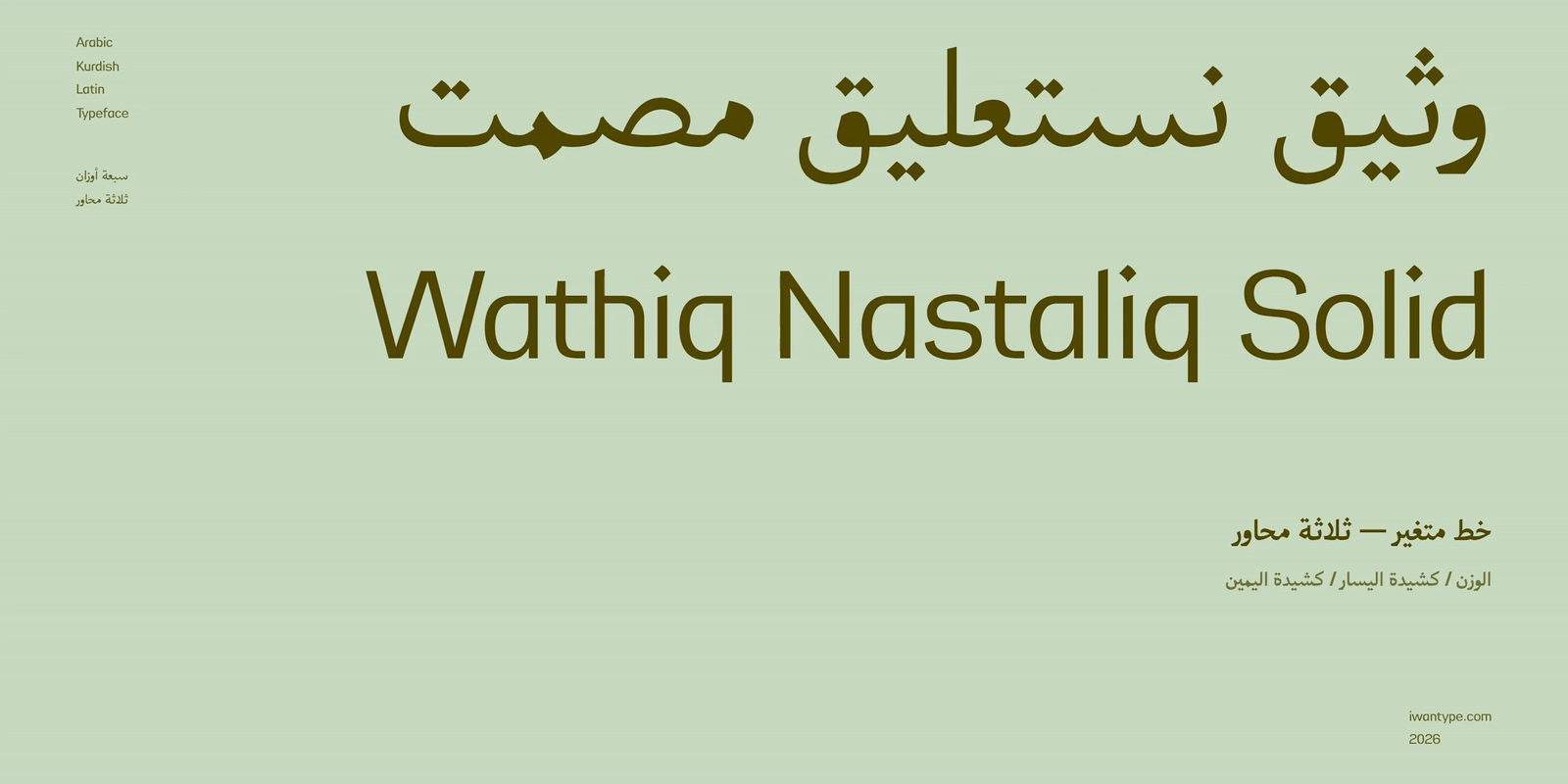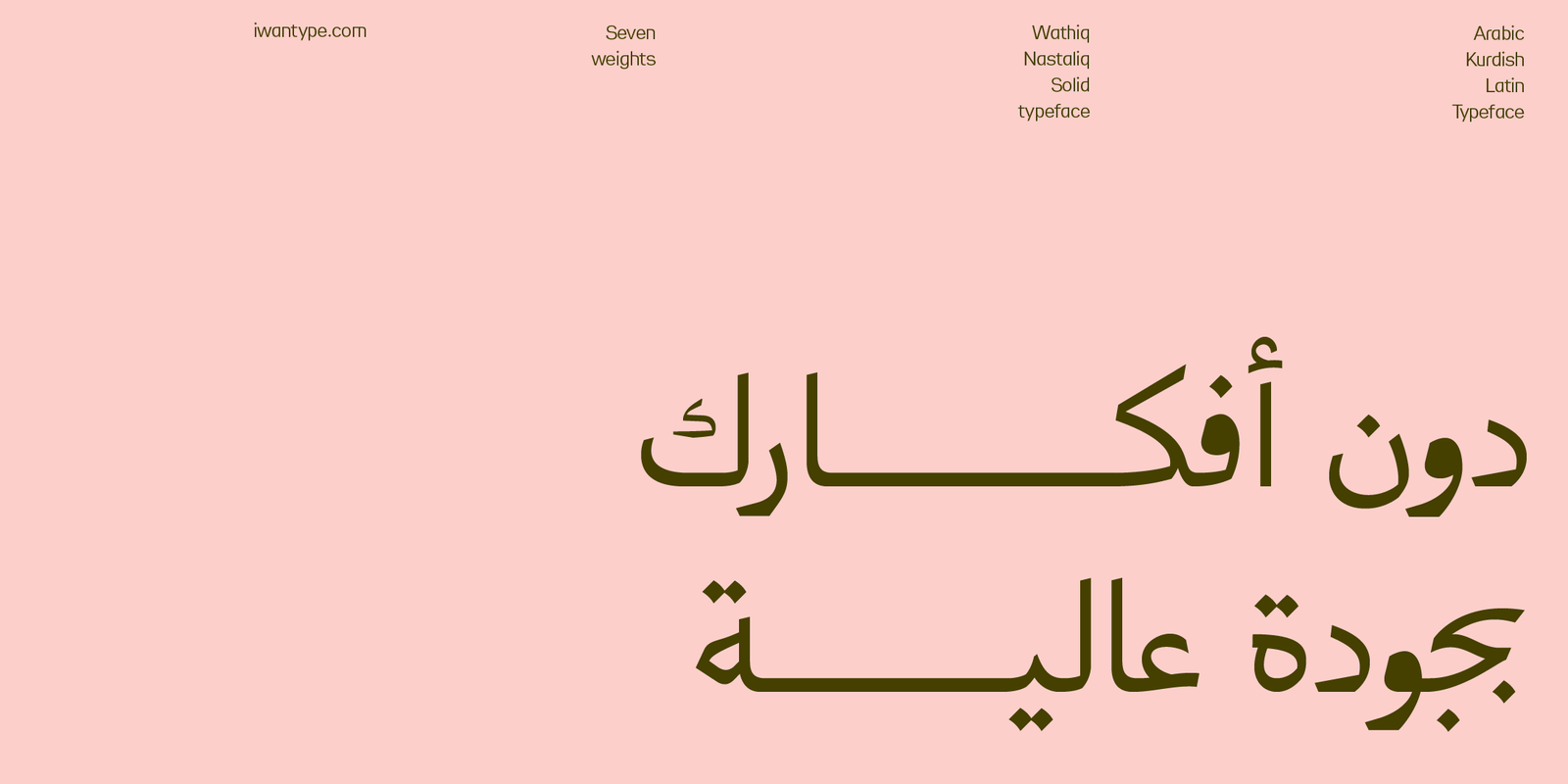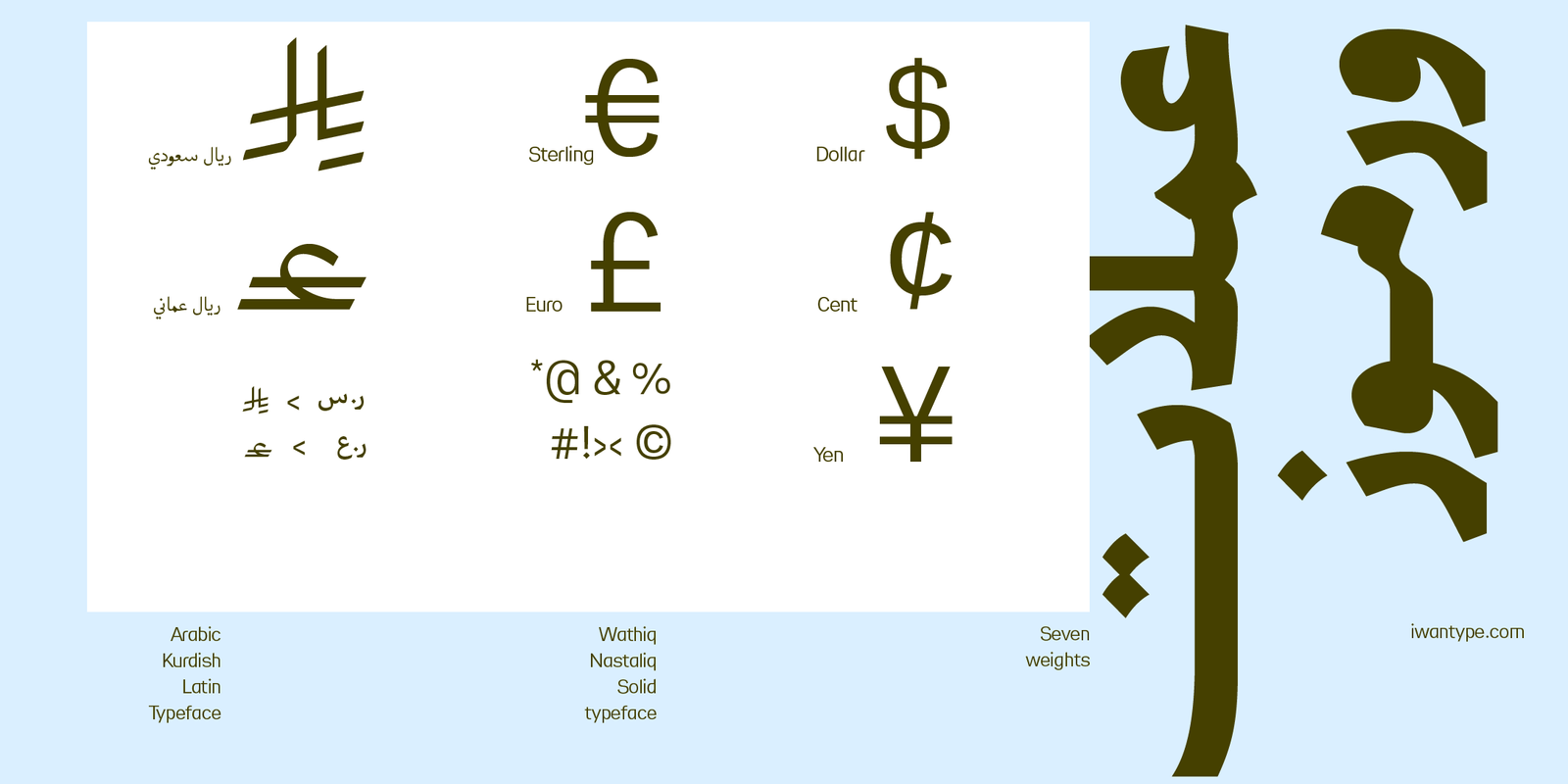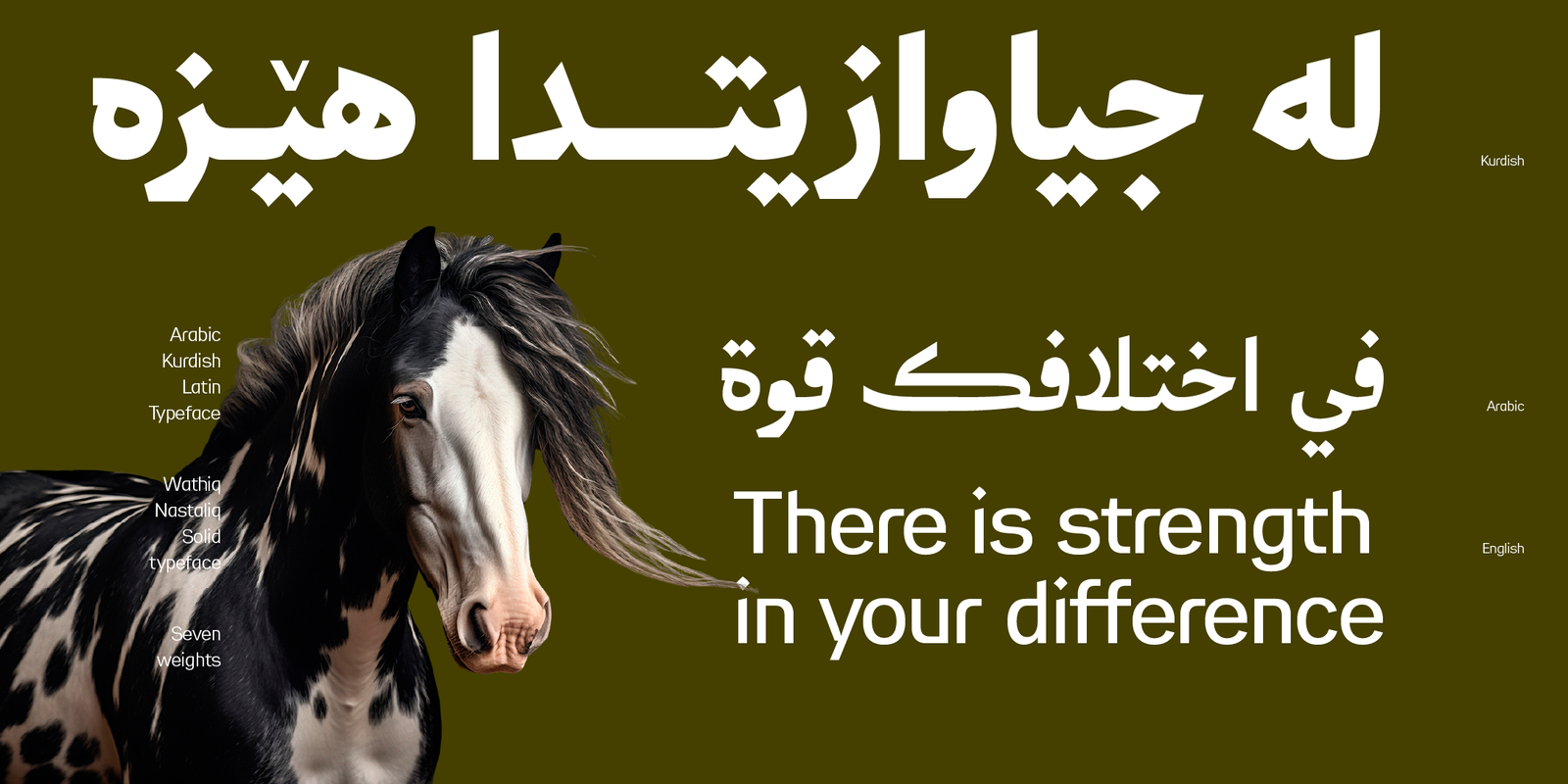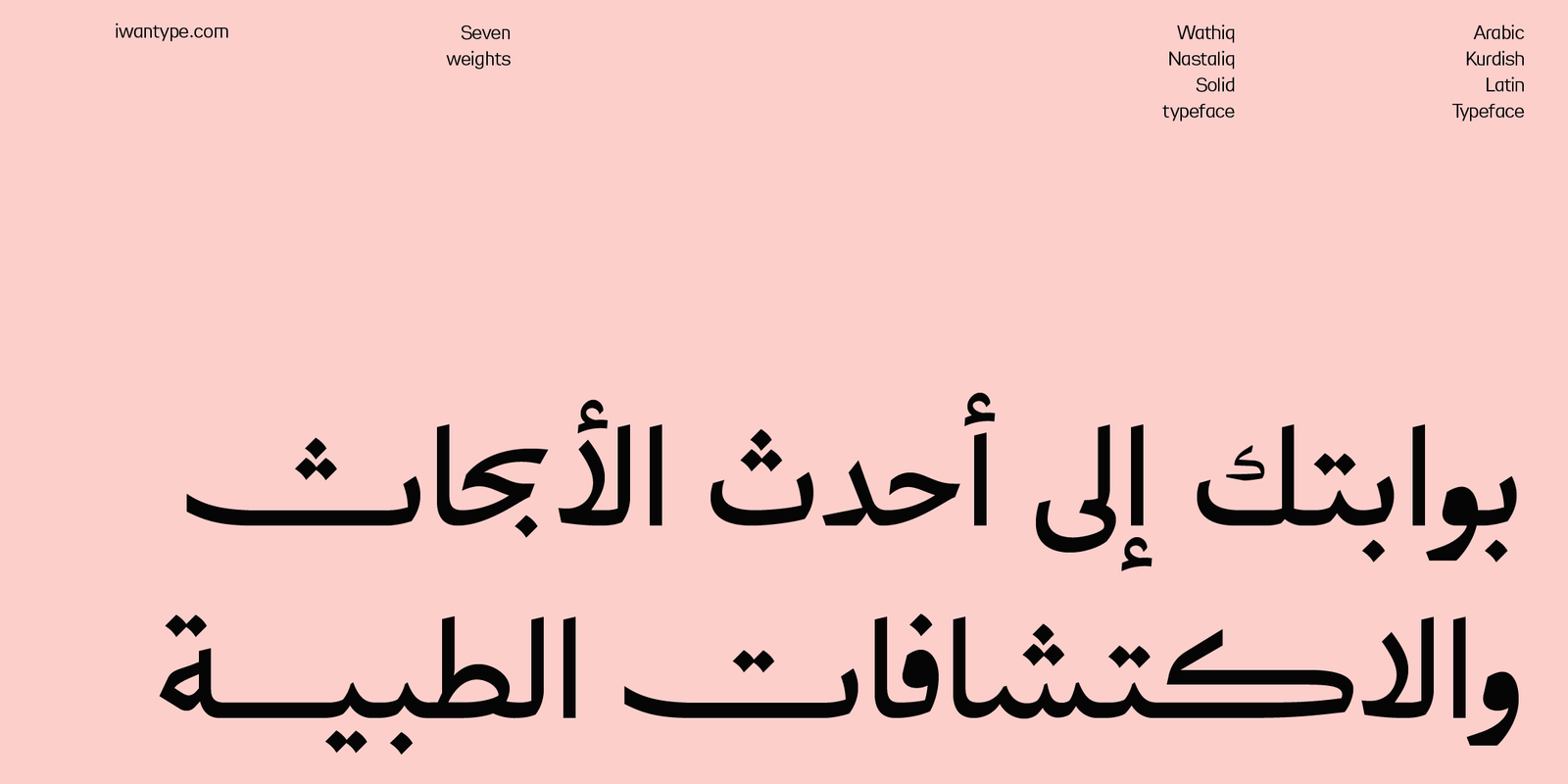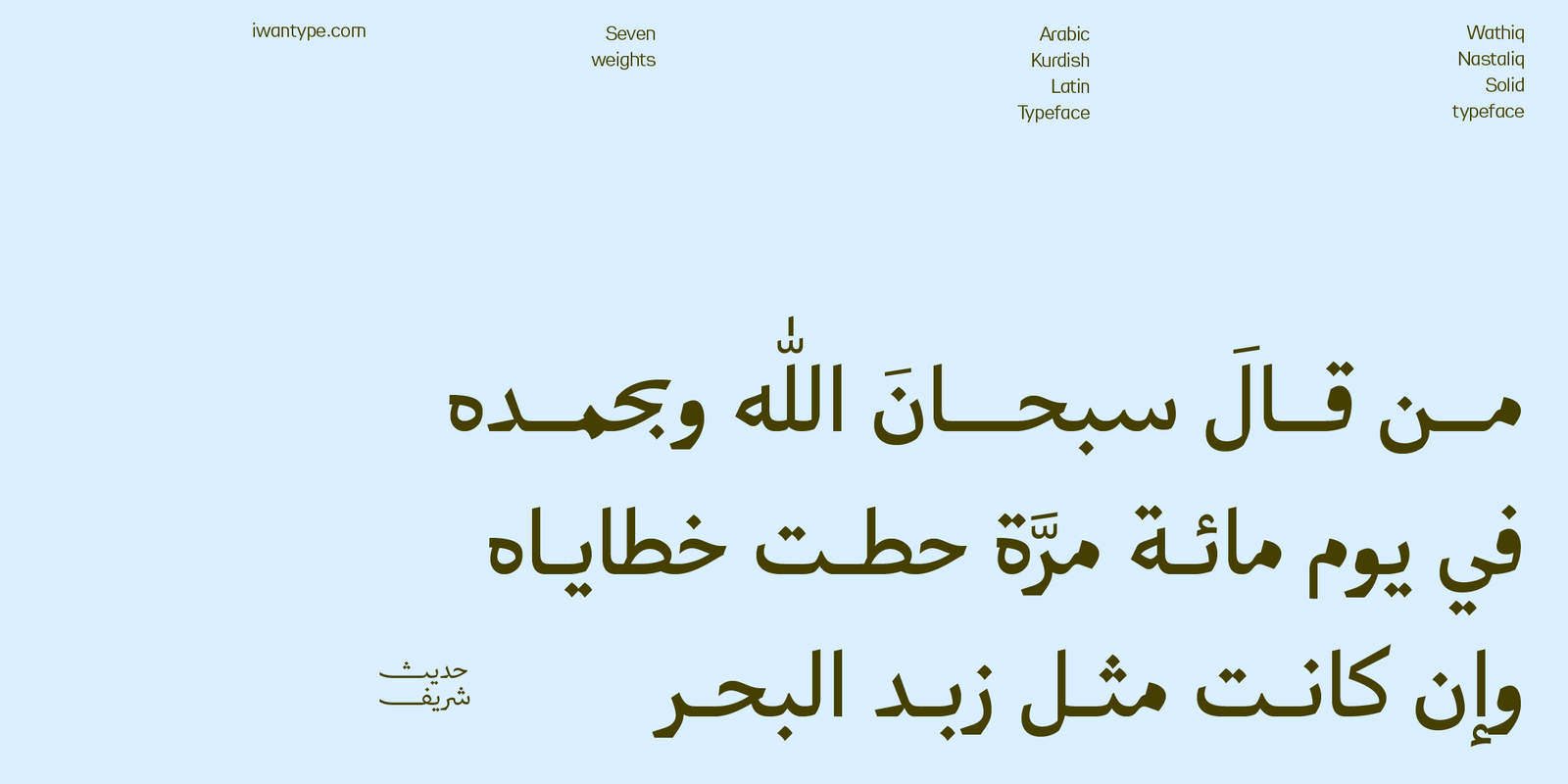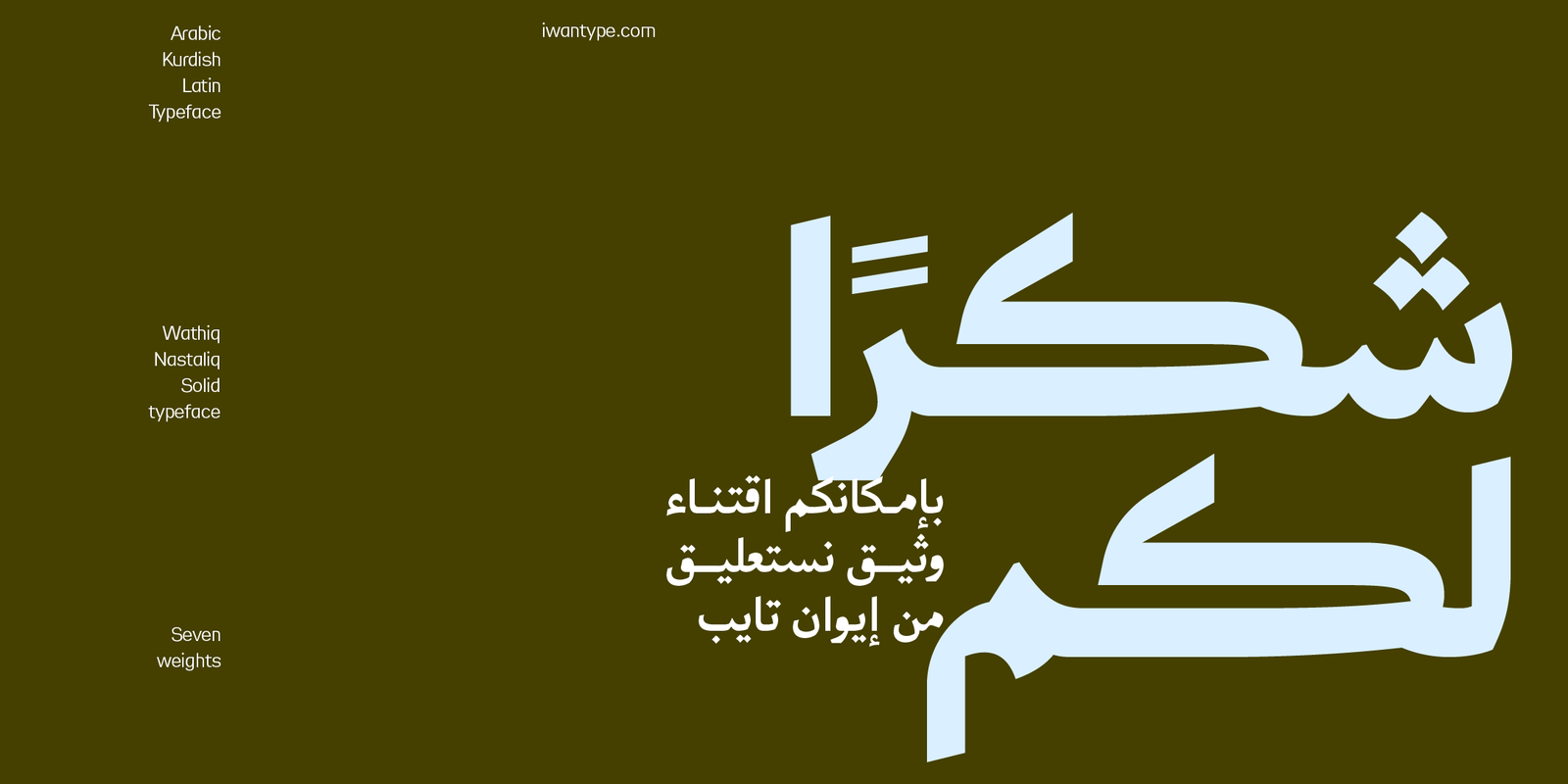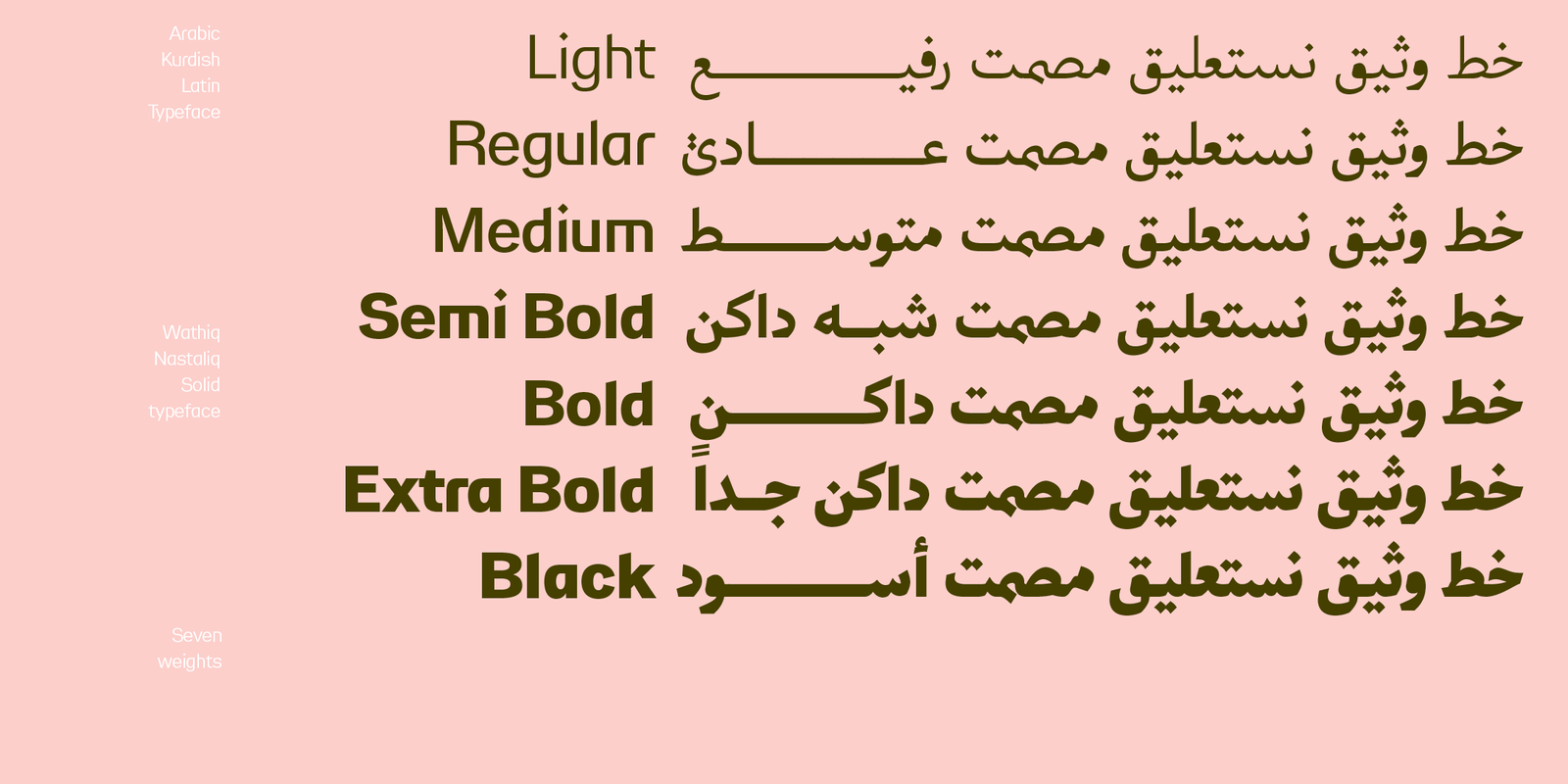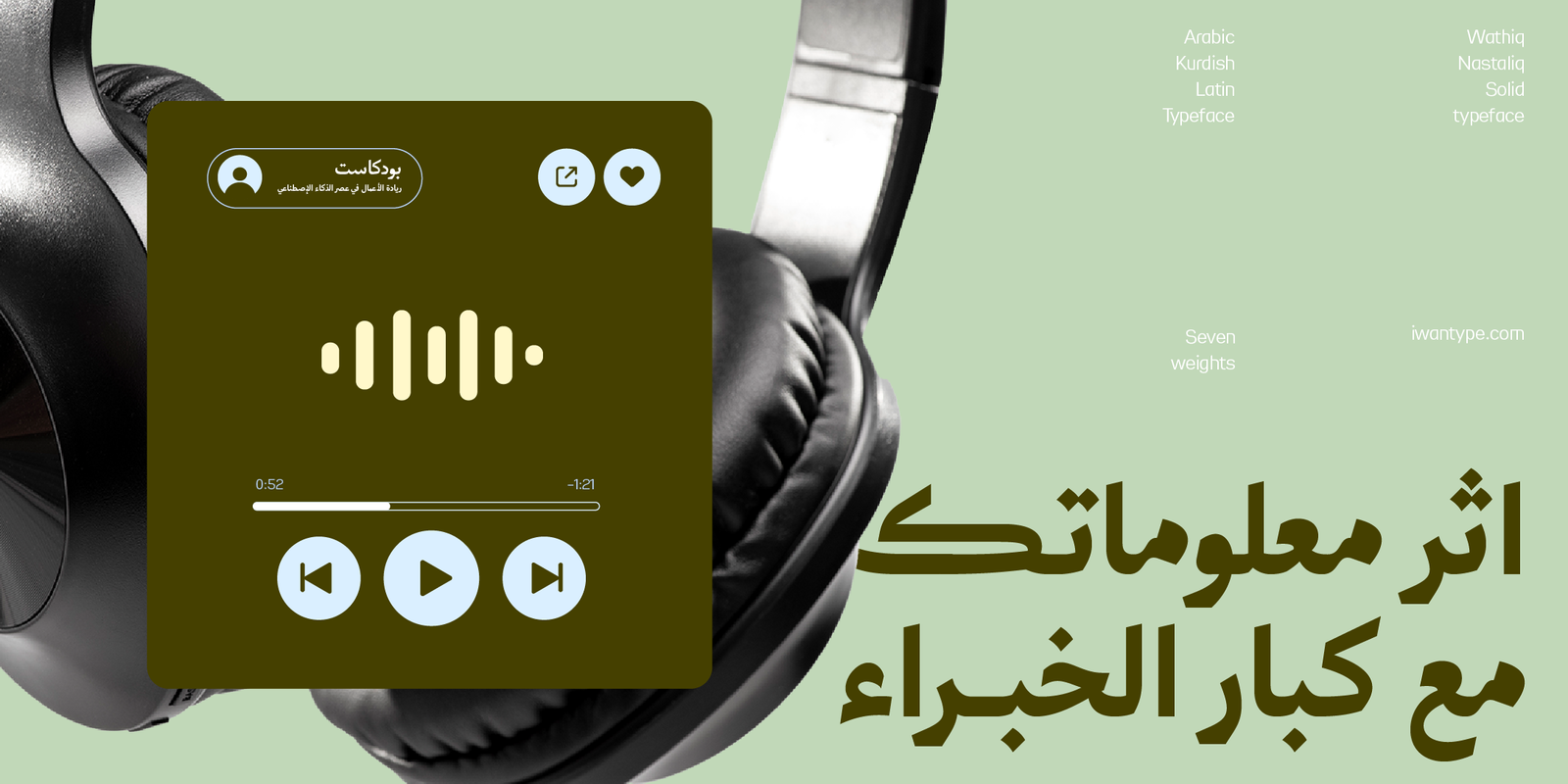
وثيق نستعليق مصمت – Wathiq Nastaliq Solid
وثيق نستعليق مصمت هو الإصدار الأقوى بصريًا من خط وثيق نستعليق، مصمم ليجمع بين وضوح الخط النسخي وانسيابية النستعليق مع حضور طباعي أكثر تأثيرًا.
يقدم الخط حلولًا للعناوين الرئيسية والمشاريع التي تحتاج إلى وضوح بصري أعلى، مع الحفاظ على الطابع الهادئ والمتزن الذي يميز عائلة وثيق.
مميزات خط وثيق:
يتضمن الخط العديد من مزايا OpenType التي تضفي عليه مرونة وتنوعًا في الاستخدام، مثل:
- أحرف مرسلة (تُفعَّل بإضافة “ءء” بعد الحرف)
- حرف ياء بنزول أقل: يقلل من نزول السطر، مما يعزز من انتظام النصوص.
- أحرف المركبة: تسهم في تحسين المظهر العام للنص وتزيد من سلاسته.
- نقاط بديلة
- يدعم رمز الريال السعودي، ويمكن تفعيله بإضافة حرف “ء” بعد كتابة كلمة “ريال”.